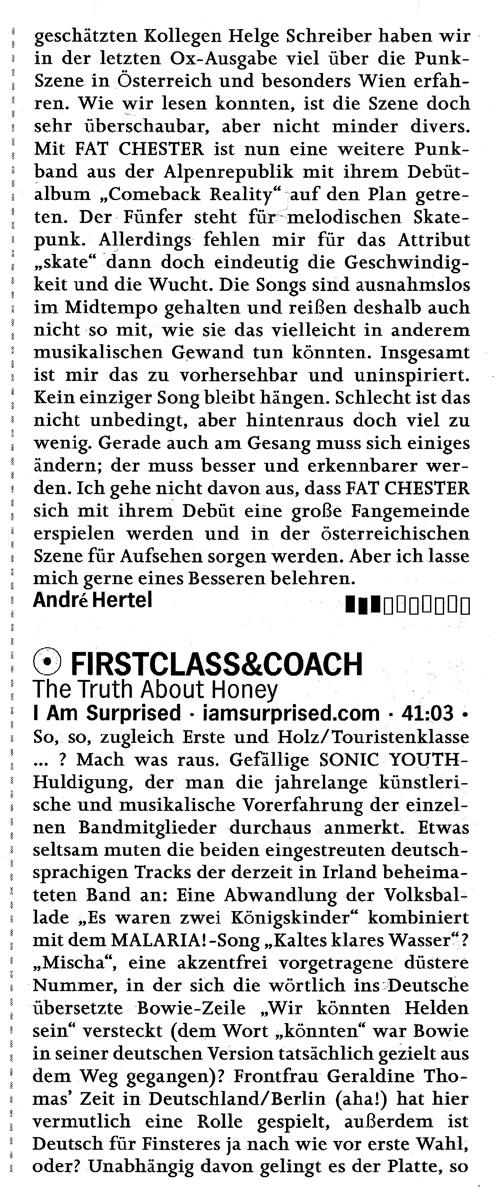
Umlaute & ß fehlerhaft
in diesem Musikmagazin sind die Sonderzeichen fehlerhaft, im Fließtext (Joanna) werden sie in einem dünneren Schnitt dargestellt. Im Namen unter dem Review in der Grotesk-Schrift (André Hertel) allerdings in der Joanna.
Was meint ihr, liegt's an einem Fehler in der PDF oder ist das im RIP passiert? Oder was anderes?
An der Schriftdatei kann es ja nicht liegen, wenn beide Fonts betroffen sind.
Dazu müsste man das pdf sehen …
Wie wurde das pdf erstellt?
Das habe ich leider nicht. Ich hab das Magazin nicht selbst erstellt, mir ist der Fehler nur als Leser aufgefallen.
Hast du trotzdem eine Idee, woran es hängt?
Das kann alle möglichen Ursachen haben, vom Font angefangen über Fehler bei der Ausgabe, falsche Codierung, alter RIP …
Es sind ja 2 verschiedene Fonts betroffen, also dürfte es daran ja schon mal nicht liegen ...